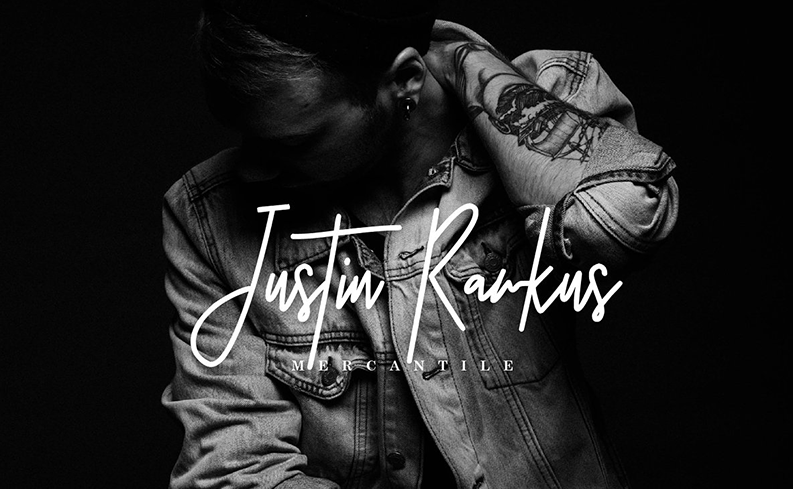
Phân loại: Cá tính
Font SVN Rawkstone là một phông chữ độc đáo thuộc bộ font SVN với phong cách mạnh mẽ và cá tính, thường được sử dụng trong các dự án thiết kế đậm chất đường phố hoặc mang tính chất nổi loạn. Với các đường nét góc cạnh, dứt khoát và đầy phá cách, font SVN Rawkstone thích hợp cho các thiết kế poster, logo hoặc ấn phẩm thời trang muốn thể hiện sự mạnh mẽ, tự do và nổi bật. Sự phá cách của font này không chỉ giúp tạo ấn tượng mạnh mẽ mà còn truyền tải cá tính riêng biệt cho từng dự án. Nếu bạn đang tìm kiếm một phông chữ thể hiện cá tính độc đáo và nổi bật, SVN Rawkstone là một lựa chọn lý tưởng.